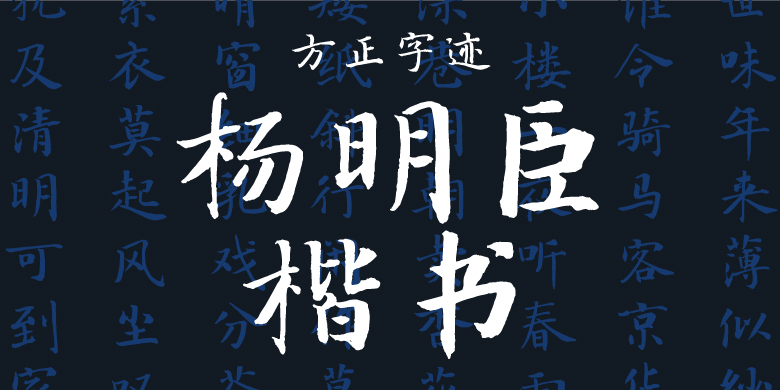
方正字迹-杨明臣楷书
方正字迹-杨明臣楷书,这款字体结构工整、笔画清晰,兼顾美观与易读性,适用于标题、正文、海报、包装、LOGO 等多种场景。字形优雅稳定,风格百搭耐看,适配日常排版与创意设计,让文字呈现更舒适、更具质感。方正字迹-杨明臣楷书一笔一画,皆是细节,以均衡的比例、流畅的线条打造舒适视觉体验,字形端正大气,风格简约现代。无论是商业设计、品牌宣传还是日常排版,都能轻松驾驭,让文字更有格调与力量。方正字迹-杨明臣楷书字体下载。
杨明臣楷书以虞褚为宗,上溯羲献,兼融隋唐碑志、赵松雪、文征明笔意,笔法劲健爽利,字法方正中有意趣,整体风格清净温和,舒展空灵,骨骼硬朗,神采奕奕,较好地实现了实用性和艺术性的和谐统一。